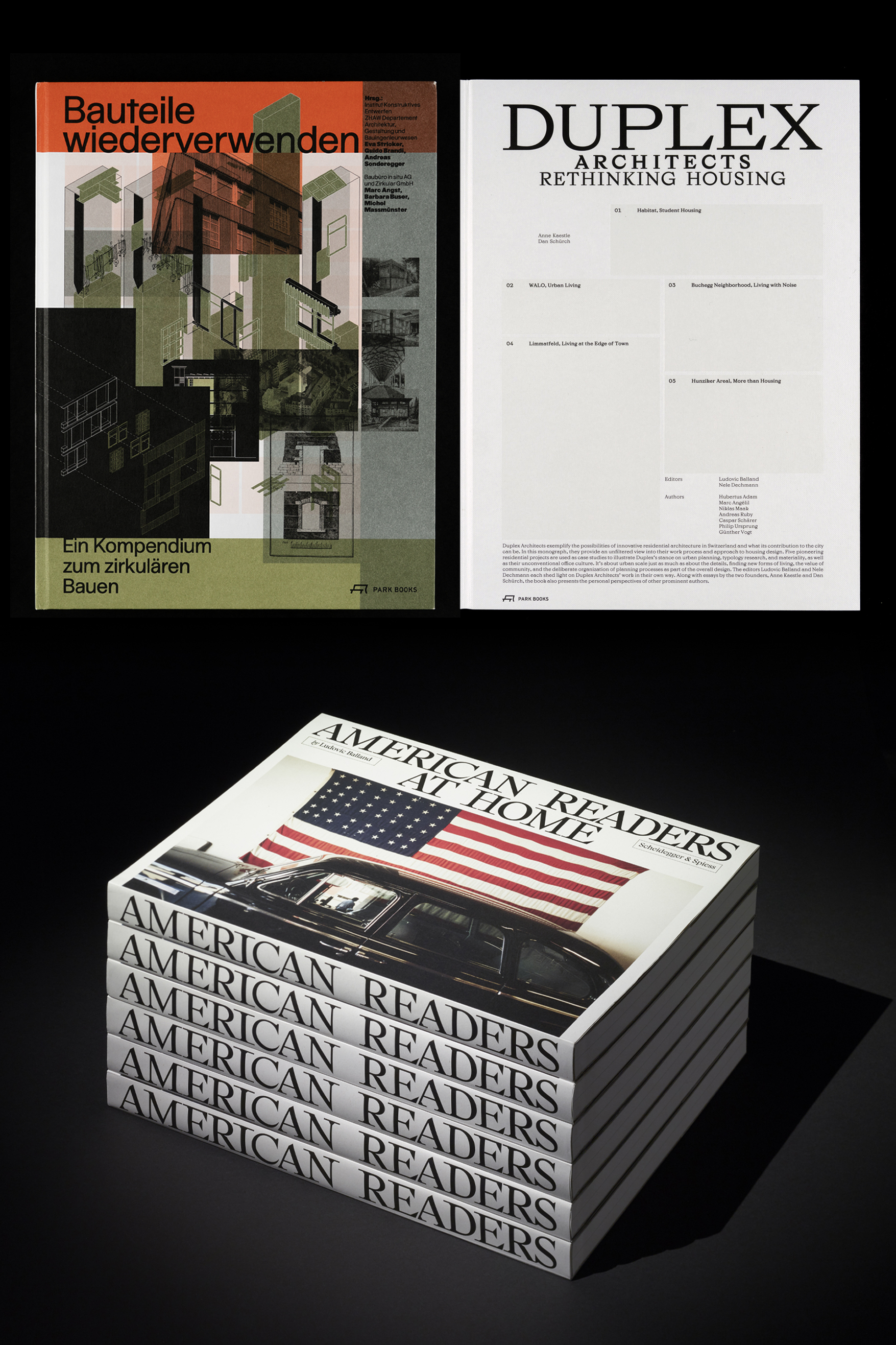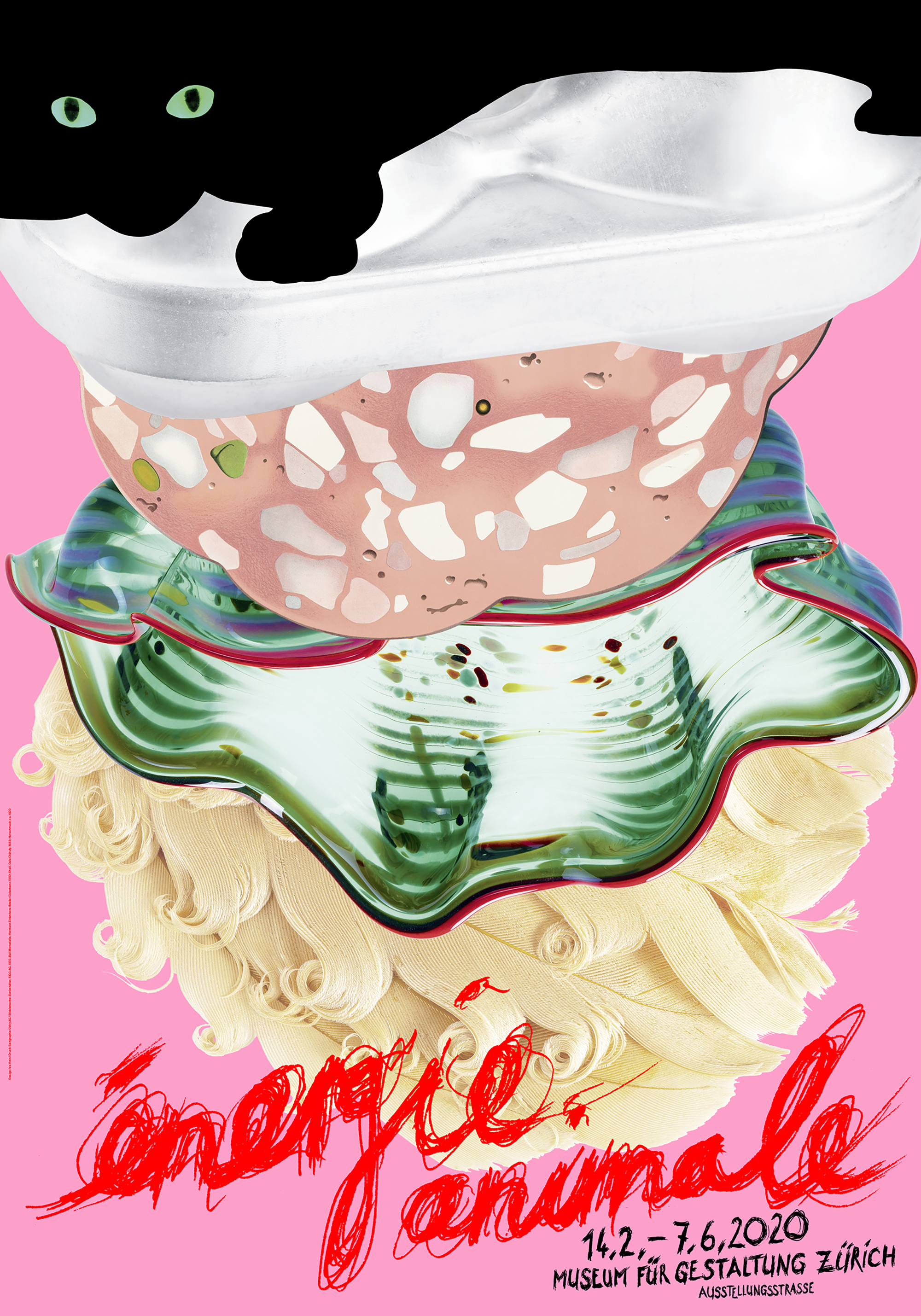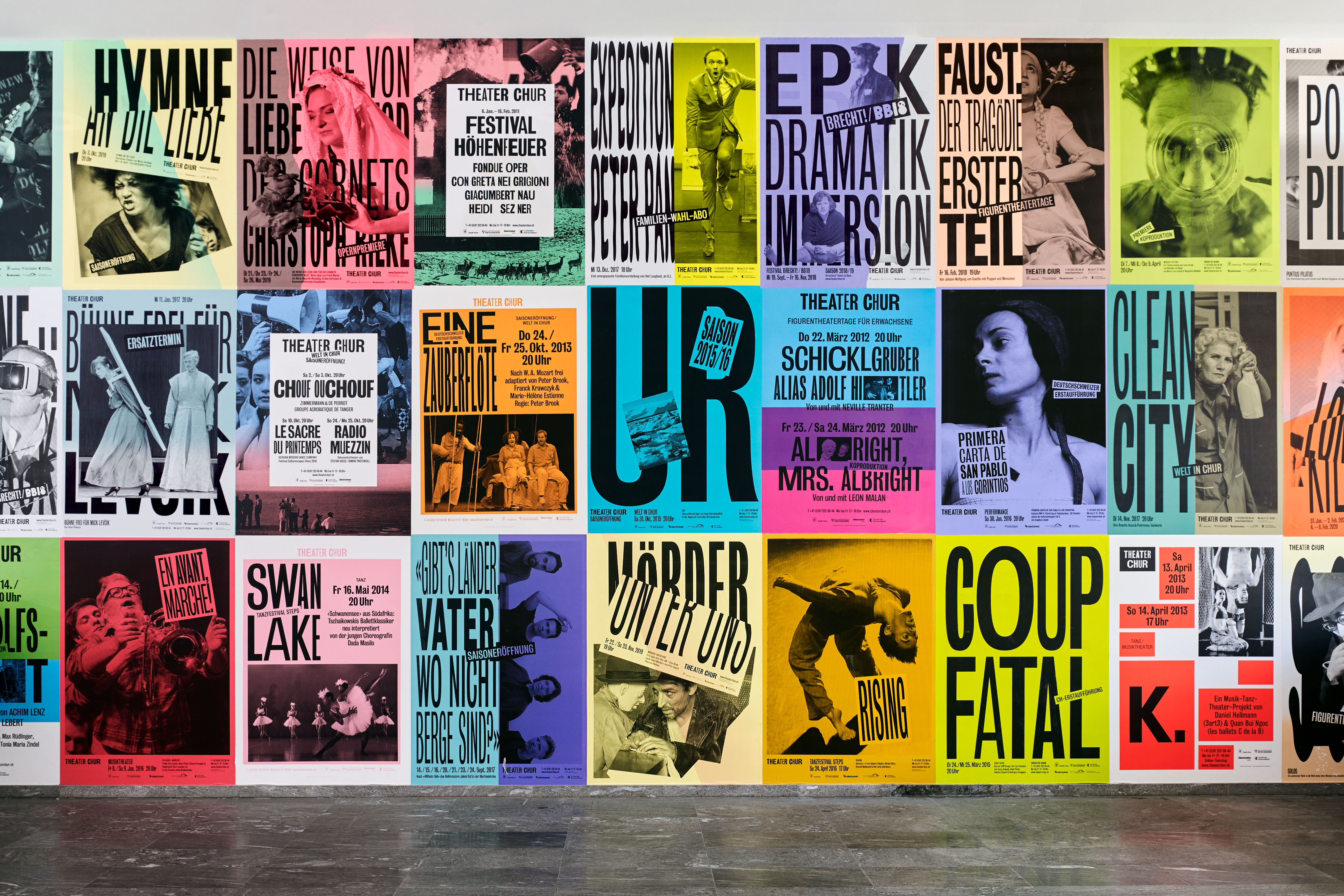
Design grafic e tipografia
Il design grafic e la tipografia èn preschents en il mintgadi sco communicaziun visuala. Els influenzeschan la cumparsa da placats, da cudeschs, da logos, d'inserats, da paginas d'internet e da bleras autras chaussas. Els intermedieschan infurmaziuns, influenzeschan opiniuns e furman valurs. Pervi da la lunga tradiziun, da la buna situaziun economica e d'in excellent nivel da scolaziun han il design grafic e la tipografia ina gronda impurtanza en Svizra. En la pratica professiunala actuala sa manifestescha in engaschament fitg ferm per la communicaziun visuala cumpletta. L'emprima mesadad dal 20avel tschientaner è sa sviluppada ina tradiziun specificamain svizra sut las noziuns «Schweizer Grafik», «Schweizer Typografie», «Swiss Typography» u «Swiss Style», ch'è daventada enconuschenta sin tut il mund ed ha ina influenza fin oz. La furmaziun visuala contemporana en Svizra sa basa sin las valurs dal stil svizzer («Swiss Style») e las sviluppa vinavant.